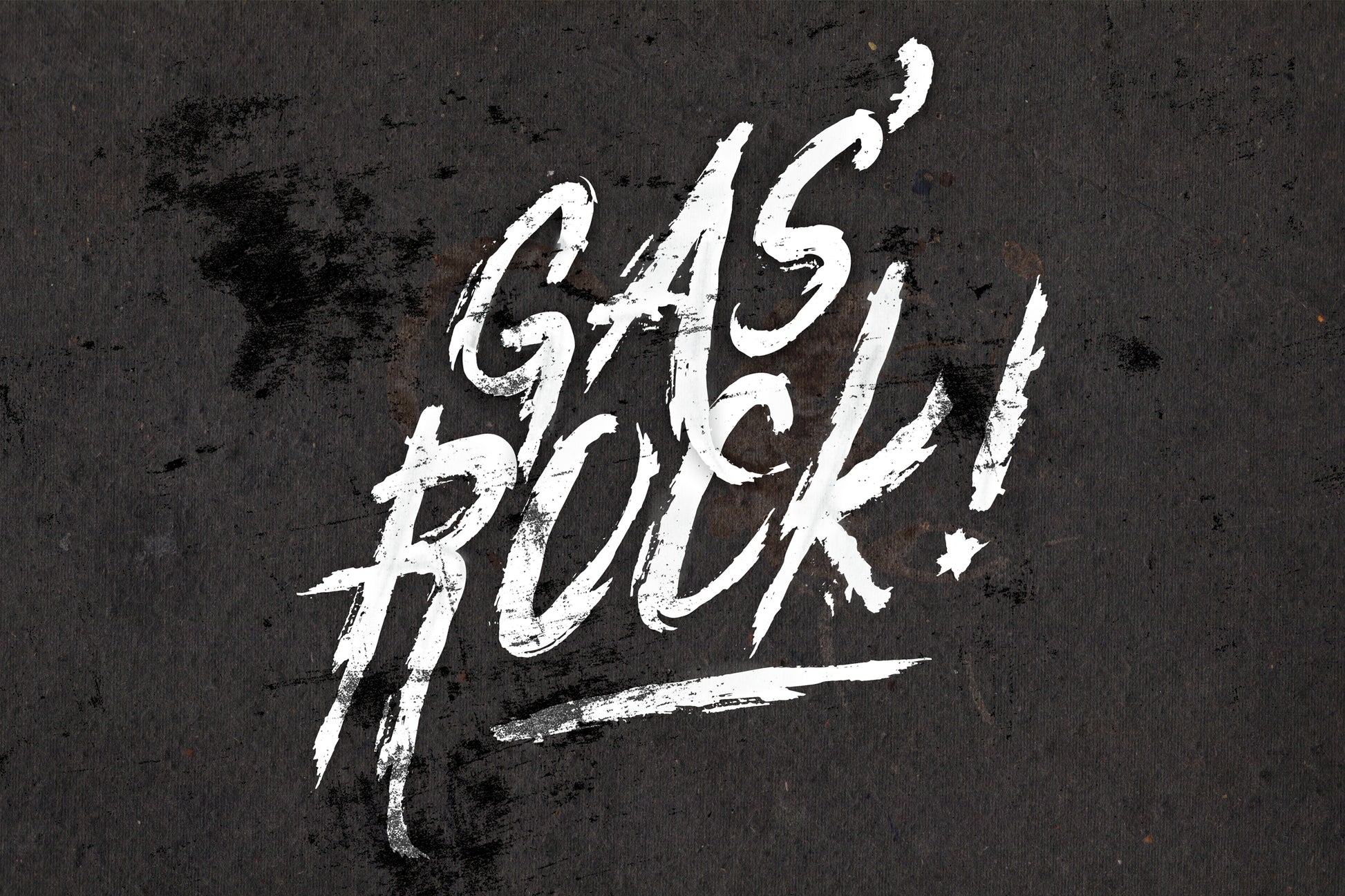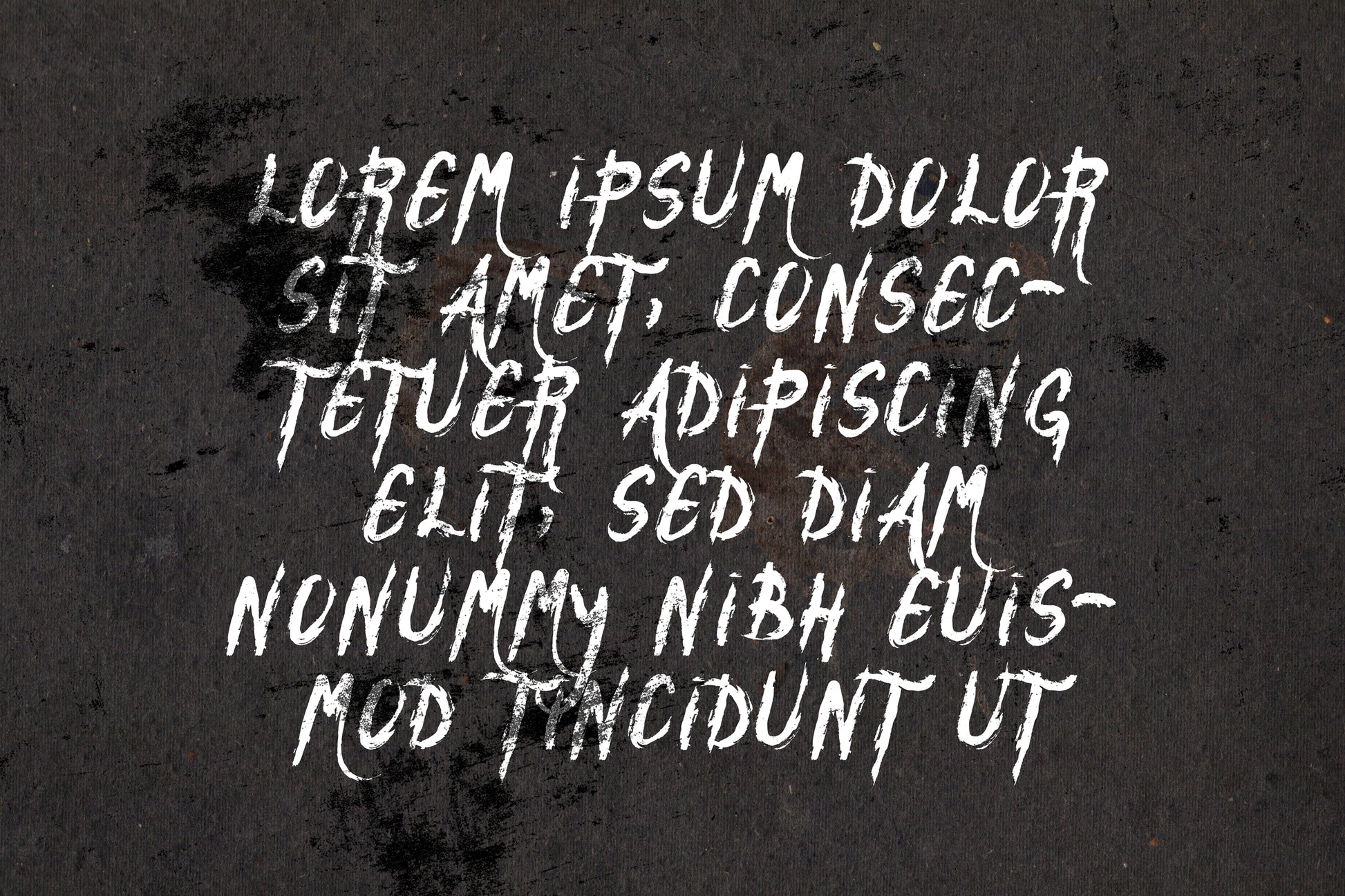
Gas'Rock!フォント
Gas'Rock!を使えば、デザインでメッセージを伝えるのが簡単になります。素敵なディスプレイ、ラベル、衣類、映画のシーン、ポスター、映画のタイトル、ライブ、アルバムカバー、ロゴなど、様々な用途にお使いいただけます。
フォントはラフな線で描かれており、ストリート風でラフな雰囲気を出したいときに最適です。